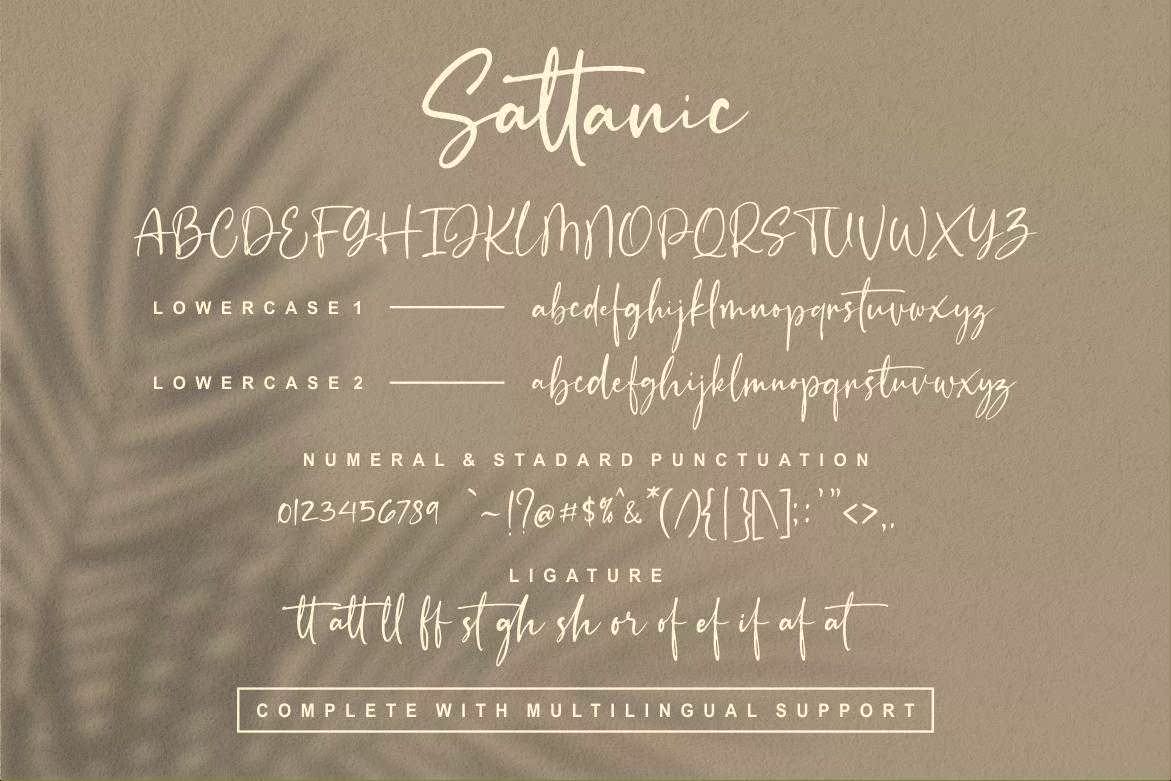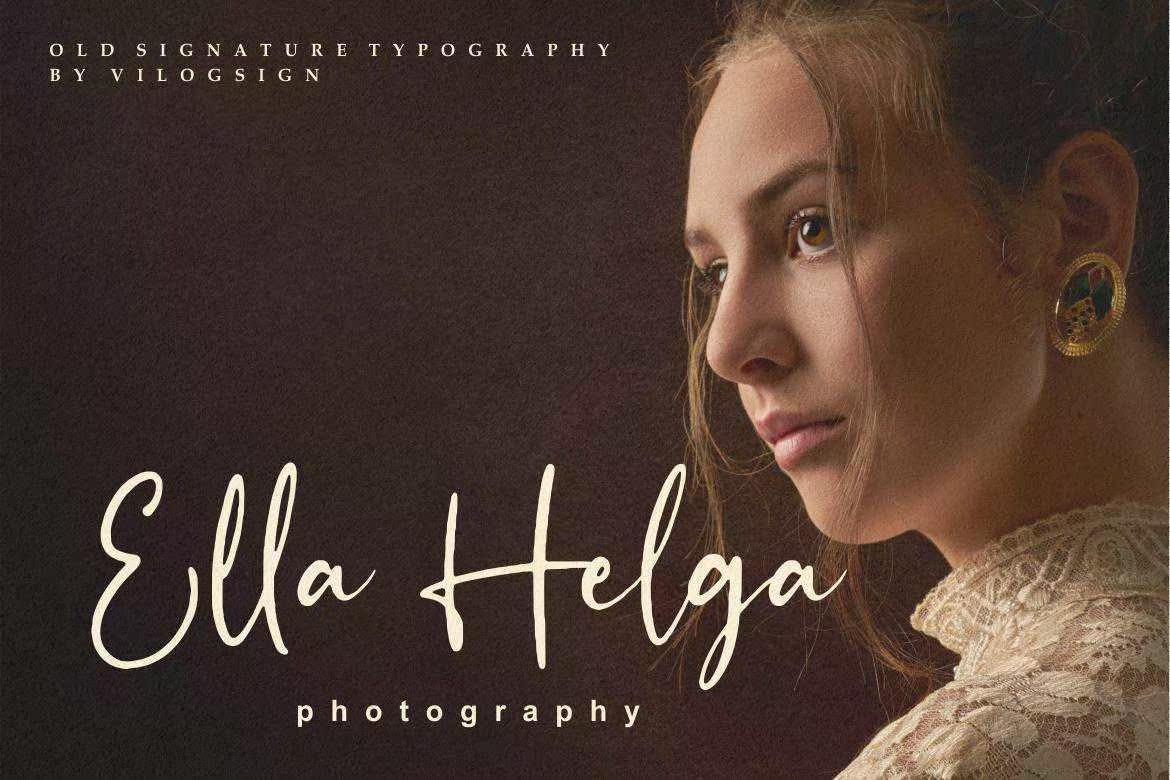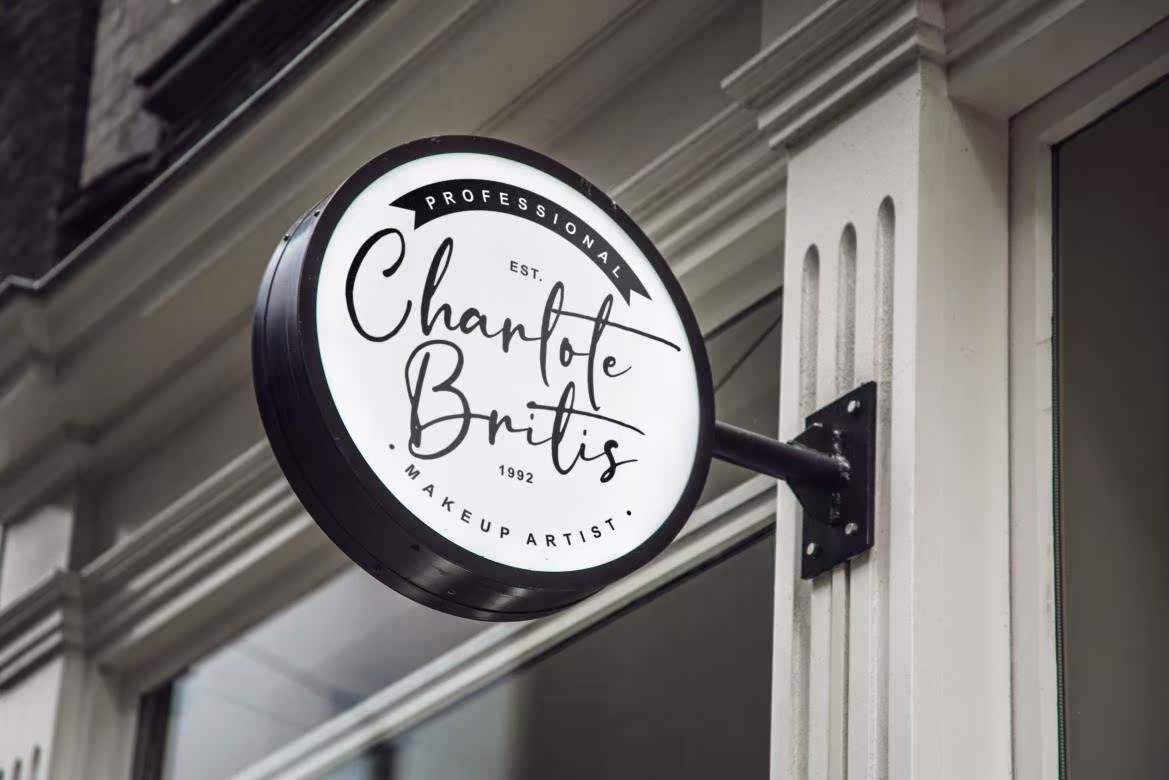
您好,,,介绍新的“Sattanic”旧签名PographyFont.Abeautiful-Vintagescriptf,使用可选的和连字符来满足您的需要。此Font使用斜体SO完成。使用内置的项目类型功能,此脚本可供您自己编写。您好,,,介绍新的“Sattanic”旧签名PographyFont。使用可选的和连字来完成您的需要。此Font使用斜体SO完成。使用内置的非字体类型功能,此脚本可以让您自己编写。